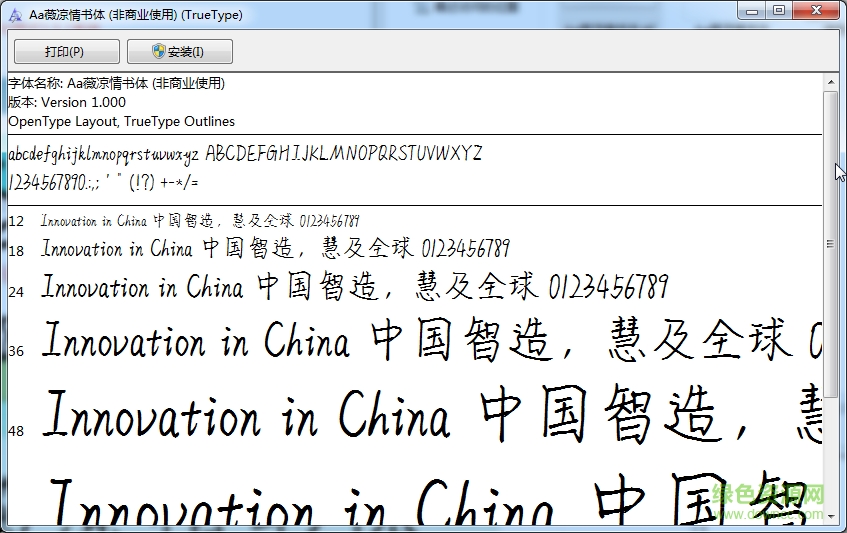
aa薇涼情書體是一款字跡纖細(xì)秀氣的情書手寫體,充滿深情的書寫很能打動(dòng)人心,筆跡分明辨識(shí)度很強(qiáng),喜歡的朋友千萬(wàn)不要錯(cuò)過(guò)啦,來(lái)綠色資源網(wǎng)即可下載喲!
薇涼情書體非商業(yè)使用,無(wú)需授權(quán),字跡簡(jiǎn)潔秀美,有鋼筆字體和藝術(shù)字體的特點(diǎn),可廣泛使用于平面設(shè)計(jì)、海報(bào)設(shè)計(jì)、名片設(shè)計(jì)等行業(yè),用戶也可設(shè)置成系統(tǒng)字體使用!
Aa薇涼情書字體具有端正、大氣的特點(diǎn),其字形俊秀、優(yōu)雅,而且還具有知性的氣息,可適用于書寫類方面的藝術(shù)設(shè)計(jì)。